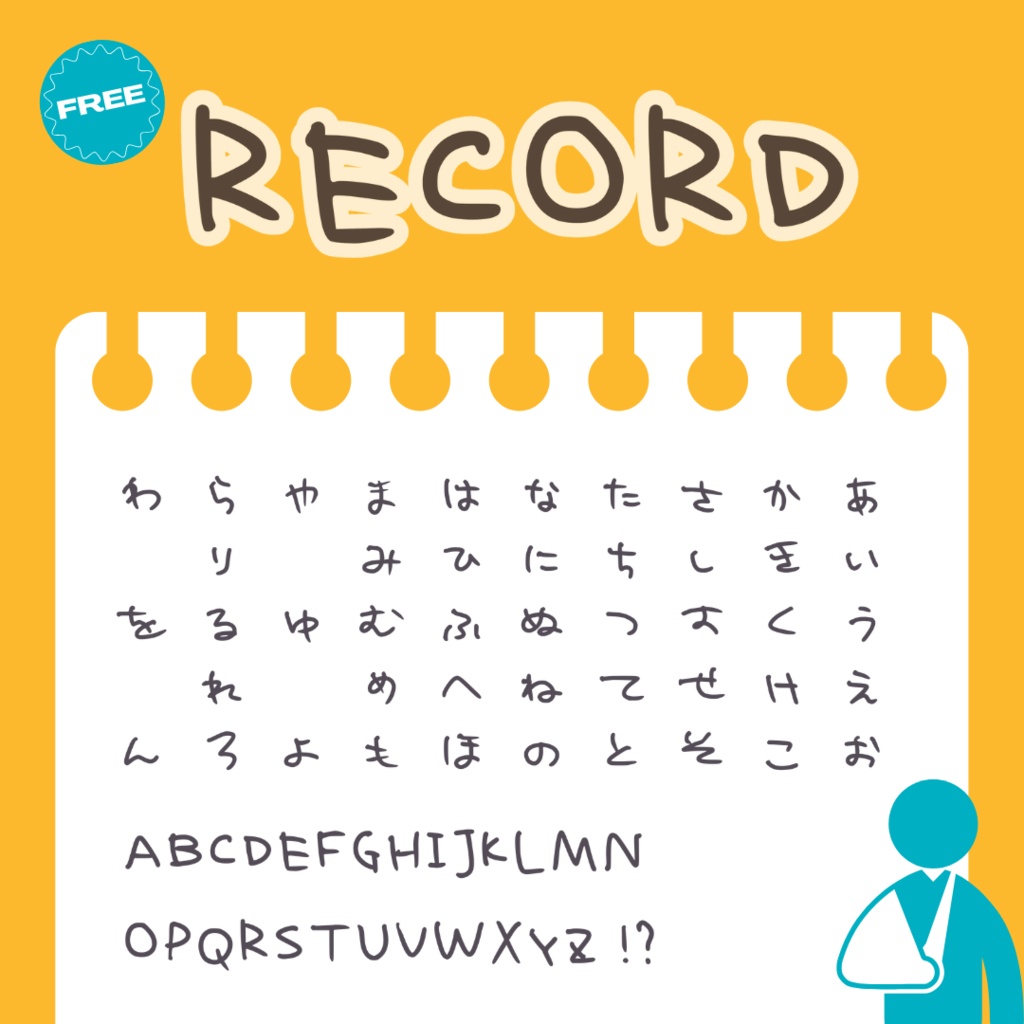
RECORD【手書き風フリーフォント】
右手首に月状骨無腐性壊死を患い、大きな創外固定器をつけている今しか書けない手の記録として制作した手書き風フリーフォントです。 不自由さの中で生まれたニュアンスをお楽しみいただけます。 子どもの字やダイイングメッセージの場面などにぜひご活用ください。
収録文字
ひらがな(※濁点・半濁点を除く) アルファベット(大文字のみ) 記号( ! ? のみ)